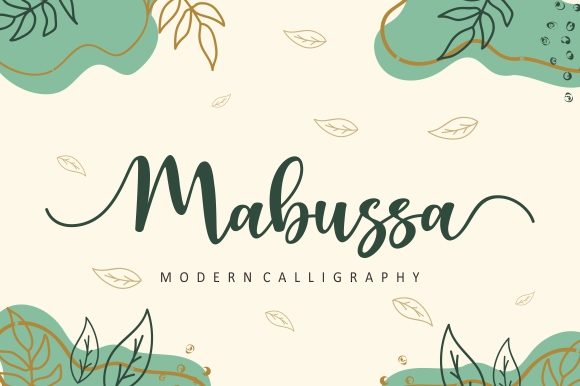
Creativefabrica Mabussa Font
[Creativefabrica] Mabussa Font
Мабусса - красивый и мечтательный рукописный шрифт.
Чёткие и хорошо закруглённые буквы делают этот шрифт шедевром.